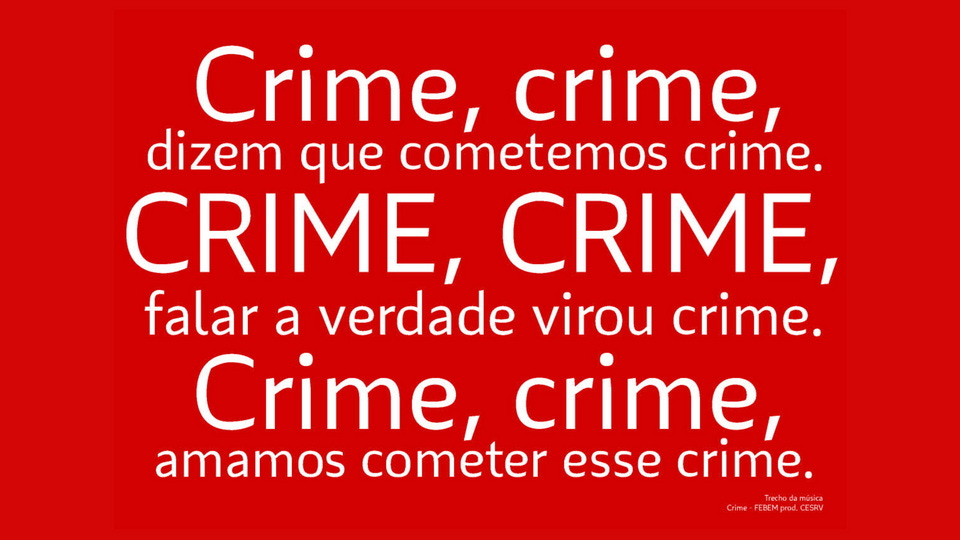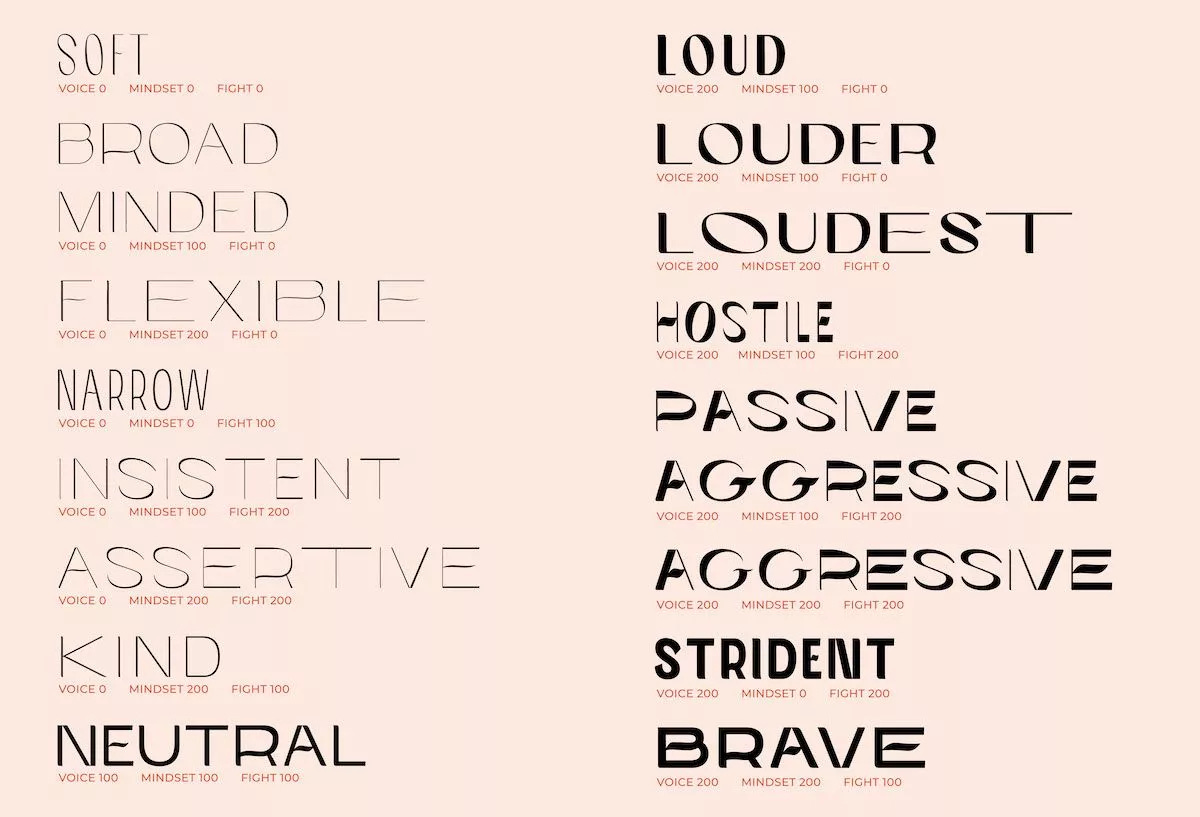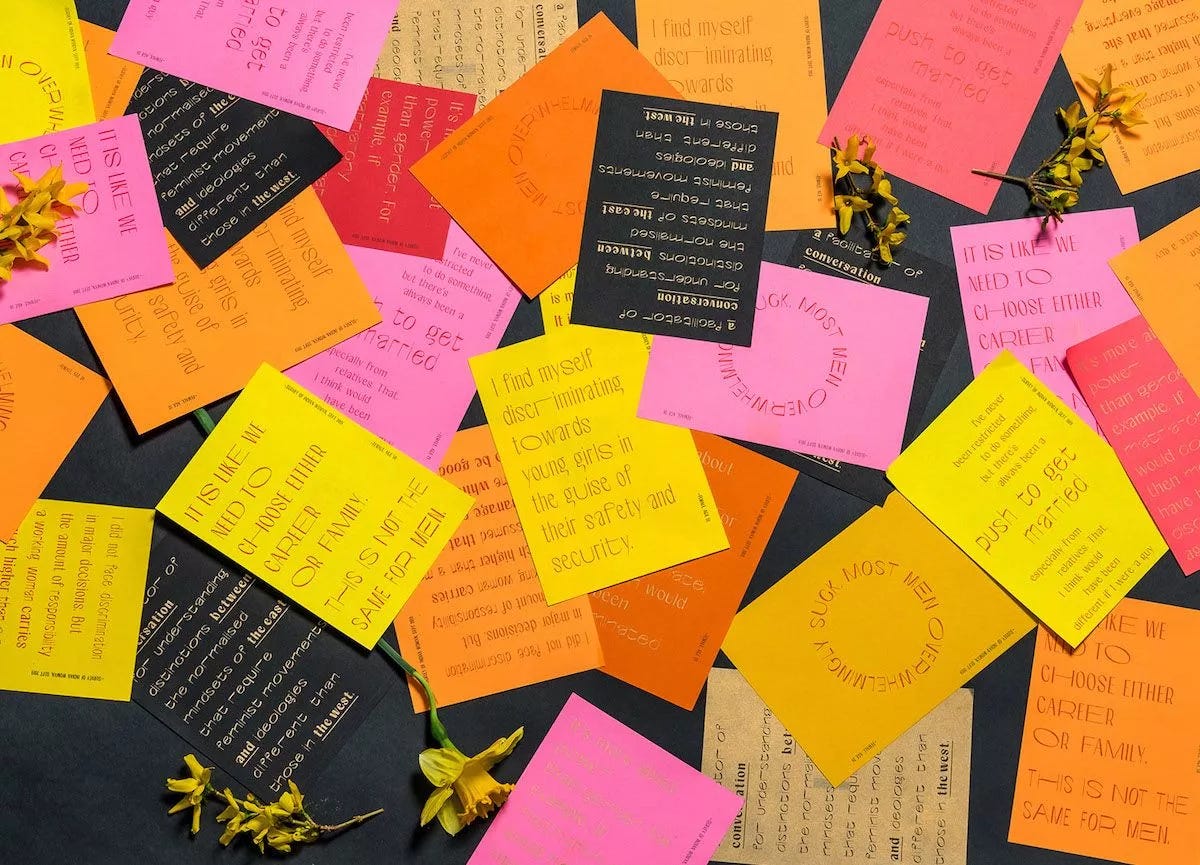
#2 tipografia e ativismo
Tempo de leitura: 5 minutos | as letras que escolhemos são quase tão importantes quanto as palavras.
a tipografia deve ser o assunto mais abordado no design gráfico depois das cores. aprendemos rápido que letras serifadas evocam seriedade e tradição, letras geométricas transmitem modernidade e as tipo display devem ser usadas com cautela. mas se podemos inferir valores como esses a uma tipografia, até onde isso pode ir? se uma tipografia pode ser considerada tradicional, será que outra pode ser considerada revolucionária?
A “Inimiga do rei” e outras tipografias para o ativismo
Conheci o trabalho do Eduardo Cazon na conferência on-line Typewknd, em 2021. Ele é o designer responsável pela Inimiga do rei - uma fonte projetada para expressar mensagens contra a opressão. O próprio autor escreve no Specimen1 da fonte:
Feita para comunicar visualmente ideias de enfrentamento à injustiças em livros contrários a opressões ou em panfletos distribuídos em um protesto.
Devido à sua aparência caligráfica e suas formas abruptas e dinâmicas, a Inimiga do rei apresenta uma nova interpretação das altamente legíveis fontes serifadas humanistas. Ela não tem medo de de ser vigorosa e grave, cheia de movimentos e tensões, ela é agressiva e combativa, mas sem perder a ternura das fontes humanistas.
A Inimiga do rei possui modulação moderada, tendo construção caligráfica de ponta chata interrompida, mas sem parecer antiga. Sua cor é escura e suas contraformas possuem quinas, devido aos seus ombros abruptos. As aberturas são amplas e os terminais são retas inclinadas, principalmente nas ascendentes e descendentes, que possuem uma altura generosa. Ela possui boa legibilidade e é confortável, mesmo tendo uma largura esguia e ritmo acelerado.
Uma vez que podemos extrair algum significado da dimensão não verbal das palavras - a escolha tipográfica -, Eduardo Cazon embarcou em uma análise histórica da tipografia que sustenta o status quo e encontrou outros projetos contemporâneos de fontes de textos projetadas para o ativismo, com o objetivo de compor uma fonte que pudesse reforçar os ideais revolucionários e antiopressão dos textos em que for empregada. A Inimiga do rei foi projetada em um software open-source, o FontForge, e está disponível para download gratuito no Fontesk. Ele descreve o processo de pesquisa e elaboração em seu Projeto de Conclusão de Curso (PCC) para a graduação em Design na UFSC. O documento completo pode ser acessado aqui. E como essa é uma seção de inspiração na makers gonna make, vou aproveitar para mostrar também outras tipografias citadas por Eduardo em seu trabalho.
Nari Variable, uma fonte para lutar contra o Tipatriarcado
Então, o que significa para uma tipografia 'ser feminista'?
Aasawari Suhas Kulkarni, designer de tipos nascida na Índia, tenta responder a pergunta em seu ensaio Entre os extremos, originalmente publicado no blog Femme Type e que eu traduzi para o português aqui.
“Neutro é normal, principal, porque é associado a sensibilidades mais masculinas e usado para transmitir mensagens políticas, usado como voz para corporações gigantes, usado para encontrar caminhos e rotular. "Neutro" se senta quietinho e dá o palco ao conteúdo da mensagem sem muito falar por conta própria. Como quando um homem branco (ou um homem brâmane de pele clara no Oriente) se levanta e diz algo ao mundo, o mundo acredita que é verdade sem fazer perguntas — o que deixa qualquer coisa que não seja neutra para ser associada com “o outro”. Se uma mulher de cor (ou uma mulher de casta baixa no Oriente) se levantar e disser a mesma coisa, isso não será necessariamente afirmado tão facilmente. O tipatriarcado (assim como o patriarcado no mundo físico) anulou nossas sensibilidades para perceber tipos neutros como limpos e seguros quando claramente tudo o que eles fazem é afirmar a normalidade e, o mais importante, se afastar da Expressão.”
Aasawari desenvolveu a tipografia variável Nari para lutar contra o que ela chama de typatriarchy, o tipatriarcado. No ensaio, ela conta como surgiu seu interesse pelo design de tipos e como também os questionamentos em relação às tipografias consideradas “neutras” pelas normas do design gráfico. Fontes sem serifa, supostamente sem uma personalidade a acrescentar, como a super-glorificada Helvetica - que atuam justamente se mantendo quietas e cedendo sempre a palavra aos homens brancos. Para Aasawari, enquanto as tipografias desenvolvidas para o ativismo continuarem a ser usadas somente para o ativismo, não derrotaremos o tipatriarcado e a desigualdade social no design. Mais do que produzir tipos de protesto, precisamos empregá-los e lutar contra a dominância da neutralidade.
obrigada por estar comigo para mais uma edição :) já estava pensando em compartilhar ‘a inimiga do rei’ quando li ‘entre os extremos’ e fiquei muito animada de trazer as duas referências juntas. assim como em relação à desigualdade social na ‘vida real’, dentro do design precisamos assumir nossa responsabilidade como “fazedores”, agentes da criatividade e da transformação. espero que essa edição possa te inspirar a tentar algo novo com a tipografia! além disso, fique a vontade para responder esse e-mail se quiser conversar, compartilhar algo ou até mesmo criticar algum ponto da newsletter. espero que esse possa sempre ser um espaço de troca.
uma amostra da fonte, normalmente uma composição de textos para evidenciar as características da família tipográfica.